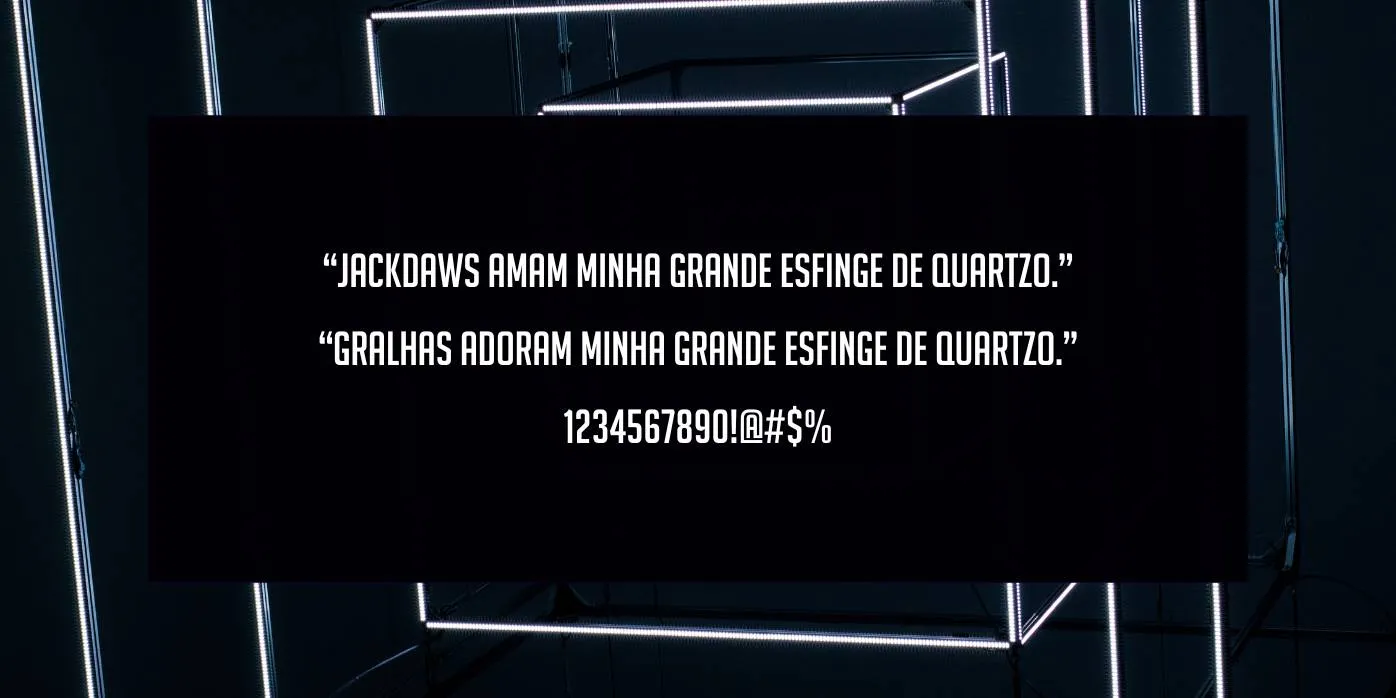
A fonte Big Noodle Titling é uma fonte sem serifa de estilo geométrico com maiúsculas estreitas e em negrito. É frequentemente usado em design gráfico para criar títulos e manchetes impactantes. A fonte tem visual moderno e sofisticado, sendo indicada para projetos que buscam transmitir uma imagem de vanguarda e elegância.
James Arboghast é o designer deste tipo de letra. Está disponível em diversas variações, incluindo versões em negrito, itálico e condensada. Isso permite que o designer crie diferentes hierarquias visuais e variações de texto, permitindo maior controle sobre o layout e a aparência do design final.
Uso da Fonte Big Noodle Titling
Essa fonte é amplamente utilizada em diversas aplicações de design gráfico de linguagem. Uma das principais áreas em que atua é na criação de materiais publicitários, como anúncios em revistas, outdoors e banners. Sua aparência arrojada e estreita o torna perfeito para destacar títulos e textos explicativos em negrito, chamando a atenção do público-alvo para a mensagem em questão.
Outro uso comum do Big Noodle Titling é em projetos de branding, como criação de logotipos e identidades visuais para empresas. A fonte transmite uma sensação de modernidade e sofisticação, que pode ser explorada para criar uma imagem vanguardista para a marca.
Essa fonte também pode ser utilizada em projetos de design editorial, como a criação de capas para livros, revistas e catálogos. Seu visual arrojado e estreito pode ser combinado com outras fontes complementares, criando um equilíbrio visual interessante e atraente. O Big Noodle Titling também é uma escolha popular para títulos e subtítulos de capítulos, ajudando a organizar o conteúdo e torná-lo mais acessível ao leitor.
Visualização da Fonte Big Noodle Titling
| Nome | Fonte Big Noodle Titling |
| Designer | James Arboghast |
| Estilo | Sem Serifa |
Qual é o tipo de fonte de titulação do Big Noodle?
Esta fonte é uma fonte sem serifa de estilo geométrico com letras maiúsculas em negrito e estreitas.
O Big Noodle Titling é uma boa fonte?
Sim, é uma fonte sem serifa versátil e elegante que pode ser utilizada em diversos projetos de design gráfico. Seu visual moderno e sofisticado o torna uma escolha popular para títulos e manchetes que buscam atrair a atenção do público de forma impactante.